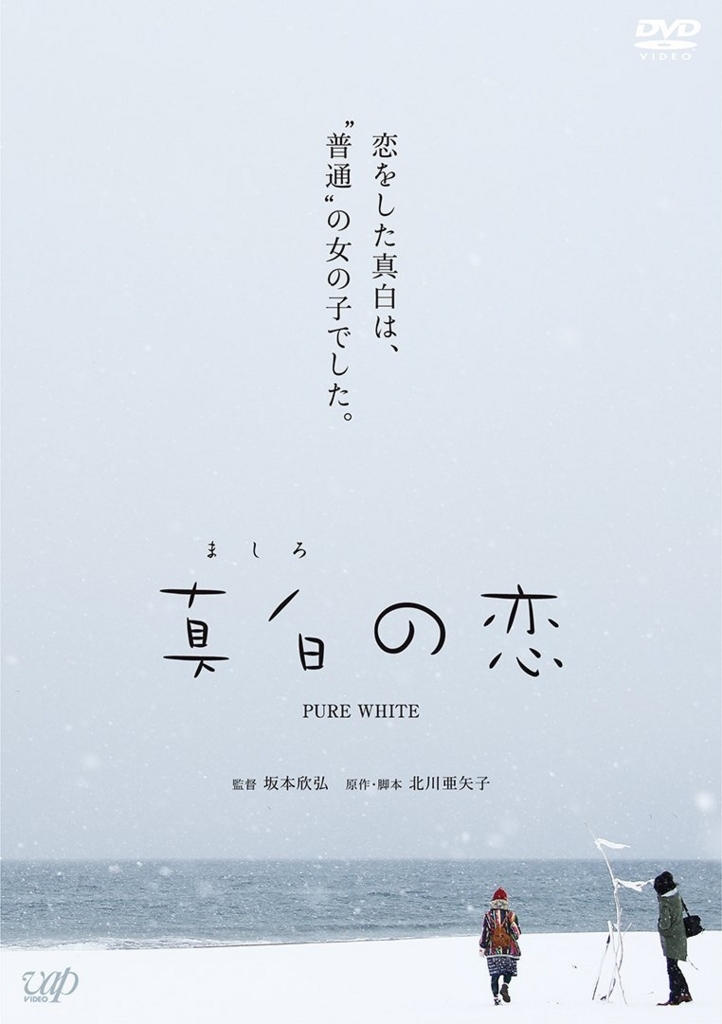
真白の恋
エレファントハウス配給、sagan pictures制作により、2017年2月2月から全国で順次公開となった邦画作品で2017年11月8日にはDVD版とBlu-ray/ブルーレイ版も発売を開始した。
渋谷真白は、生まれてからこれまで、家族と共に富山で暮らしている。
見た目にはそれとわからないが、真白には、ごく軽度の知的障がいがある。
日常生活に支障はなく、現在は父の営む自転車店の店番をしたり、飼い犬の世話をしたりと、元気に暮らしている。
ある日、兄の結婚式で神社を訪れた真白は、 東京からやって来たフリーカメラマン、油井景一に出会う。
真白の、生まれて初めての恋。 応援する人、心配する家族。 その中で真白は何を感じ、どう成長していくのか…。
自然豊かな富山に暮らす、ひとつの家族の、「優しさ」と「葛藤」を描く。
真白の恋のロゴにダイナフォントのクラフト童が採用
「真白の恋」のロゴとしてダイナフォントのクラフト童が採用されている。
クラフト童の特徴
水彩筆で描かれたような筆遣いで、起筆から終筆まで自由で天真爛漫なイメージを感じさせる書体。繊細なストロークは、子供向けのハガキや絵本、書籍などのデザイン性が高いサブタイトルや文章にオススメ。